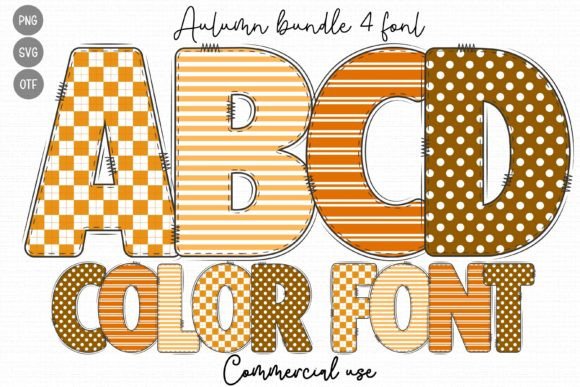
Autumn Font
Autumn Font – خط أنيق بلمسة الخريف
أضف لمشاريعك لمسة دافئة وساحرة مع Autumn Font، الخط المثالي لتصاميم المواسم والأعمال الإبداعية. يتميز بتصميم أنيق يجمع بين الطابع الكلاسيكي والحديث، مما يجعله مثاليًا لاستخدامات متعددة، مثل:
يأتي الخط بجودة عالية وأحرف متوازنة لضمان تجربة استخدام سلسة وإبداعية. اجعل لمسات الخريف تنبض بالحياة في تصاميمك مع Autumn Font! ????✨